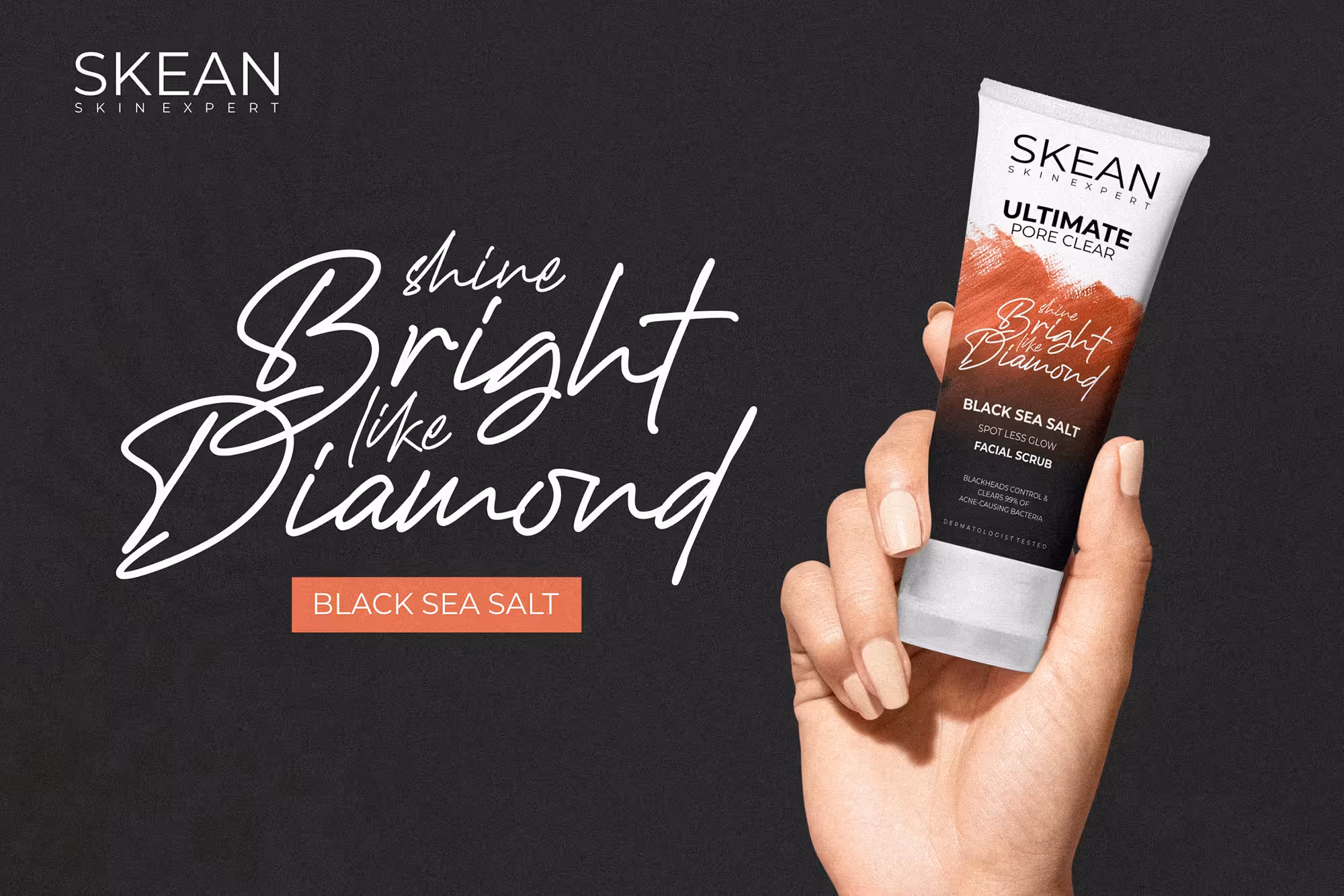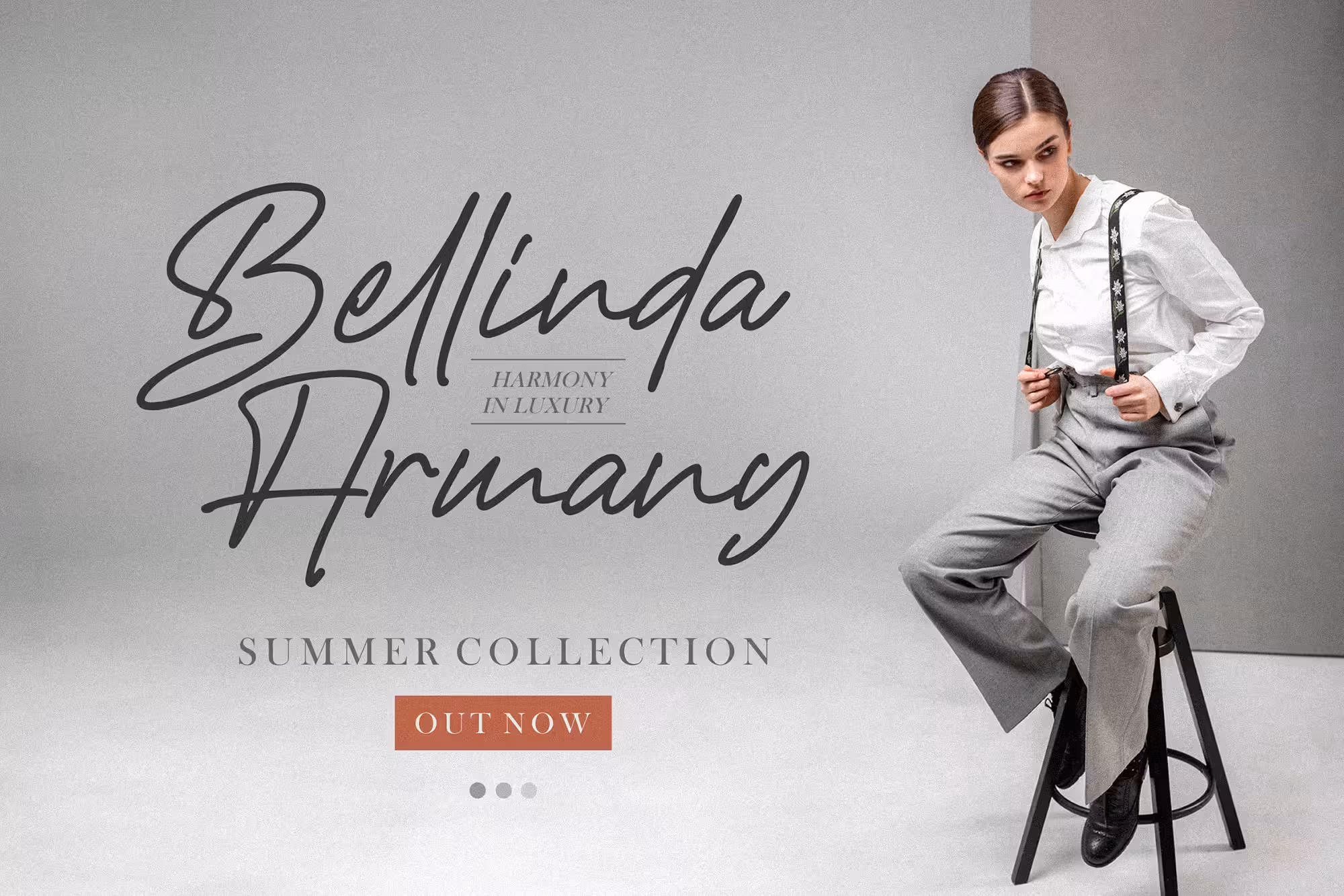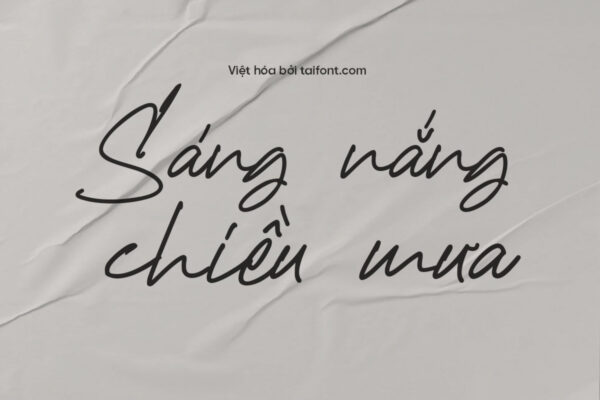
Giới thiệu về Font TF Hadejah Signature Việt hóa
TF Hadejah Signature Việt hóa là một font chữ viết tay (script font) nổi bật với thiết kế mềm mại, tròn trịa và đầy duyên dáng. Font này mang đến vẻ ngoài tinh tế, lãng mạn và rất riêng, gợi cảm giác như một chữ ký được viết tay một cách tự nhiên và đầy cảm xúc, lý tưởng để tạo điểm nhấn độc đáo và thu hút mọi ánh nhìn trong các thiết kế đòi hỏi sự cá tính và sự thanh lịch.
Với đặc điểm là nét viết tay mềm mại, phong cách tự nhiên và tính thẩm mỹ cao, Hadejah Signature là lựa chọn hoàn hảo cho các ấn phẩm muốn truyền tải sự nhẹ nhàng và phong cách, đặc biệt là trong các lĩnh vực:
- Thiết kế mỹ phẩm: Hoàn hảo để sử dụng trên bao bì, nhãn mác, hoặc các ấn phẩm quảng cáo của các sản phẩm làm đẹp, mỹ phẩm cao cấp. Font này giúp truyền tải vẻ đẹp tinh tế, sang trọng và độc quyền của sản phẩm, nâng tầm giá trị thương hiệu.
- Thiết kế thiệp: Lý tưởng để viết lời mời, lời chúc, hoặc các thông tin chi tiết trên thiệp cưới, thiệp sinh nhật, thiệp kỷ niệm. Nét chữ mềm mại của font sẽ biến mỗi tấm thiệp thành một tác phẩm nghệ thuật, mang đậm dấu ấn cá nhân và sự lãng mạn, trang trọng.
- Thiết kế logo và nhận diện thương hiệu: Phù hợp cho các thương hiệu muốn truyền tải sự tinh tế, độc đáo và một chút hoài cổ, đặc biệt là các thương hiệu liên quan đến ẩm thực, đồ handmade, hoặc các sản phẩm mang tính di sản.
- Thiết kế nội dung và trích dẫn: Tuyệt vời để tạo các câu trích dẫn đầy cảm hứng, slogan hoặc các dòng chữ cần sự nổi bật và mang tính biểu cảm trên mạng xã hội hoặc các ấn phẩm khác, đặc biệt khi kết hợp với hình ảnh mang hơi hướng cổ điển hoặc nghệ thuật.
Với TF Hadejah Signature Việt hóa, bạn có thể dễ dàng thổi hồn tinh tế, sang trọng và vẻ đẹp hoàn hảo vào các thiết kế, tạo ra những sản phẩm không chỉ đẹp mắt mà còn đầy cảm xúc và sức hút đặc biệt.